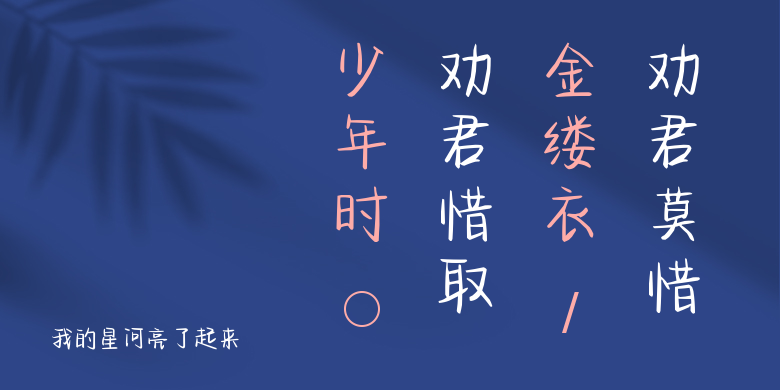
我的星河亮了起来
我的星河亮了起来,这款字体结构工整、笔画清晰,兼顾美观与易读性,适用于标题、正文、海报、包装、LOGO 等多种场景。字形优雅稳定,风格百搭耐看,适配日常排版与创意设计,让文字呈现更舒适、更具质感。我的星河亮了起来一笔一画,皆是细节,以均衡的比例、流畅的线条打造舒适视觉体验,字形端正大气,风格简约现代。无论是商业设计、品牌宣传还是日常排版,都能轻松驾驭,让文字更有格调与力量。我的星河亮了起来字体下载。